You Know It Now Show It Retro School SVG
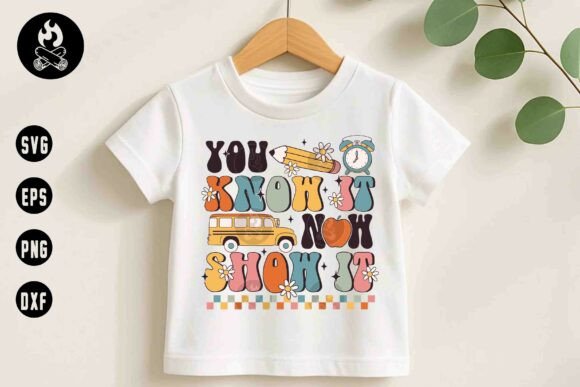
Znalezienie odpowiednich elementów projektu może być wyzwaniem, ale You Know It Now Show It Retro School SVG oferuje wyjątkową kolekcję, która natychmiast ulepszy Twoją pracę.
Precyzyjnie wykonany, You Know It Now Show It Retro School SVG zapewnia czyste wektory, płynną typografię i licencję komercyjną dla Twojego spokoju.